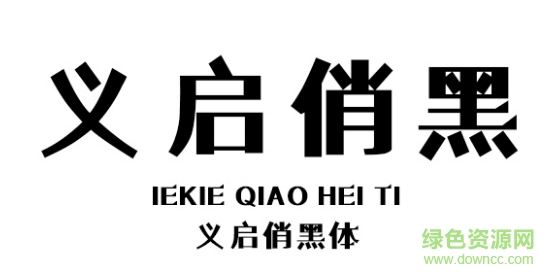
義啟俏黑體是一款非常有特色的一款黑體字體,這款字體字形俊俏可愛,非常適用于美工設計方面的字體,喜歡的朋友歡迎來綠色資源網(wǎng)免費下載使用。
誰說黑體不能俊俏?我就是我,是個性不一樣的俏黑。它與黑體結(jié)構(gòu)相同,但點畫粗壯且粗細一律,起止皆方,氣象豐滿。字體空間的分配,色彩度的感應變化及字體視覺真實與假象的運用,并且結(jié)合黑體與宋體的特點與理解,最終設計出這款“義啟俏黑體”。